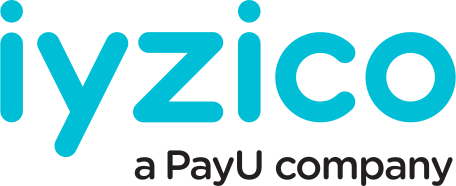
İyzico Logo Font'u Bilen?
İyzico'nun yazı fontu çok hoşuma gitti. Bu font'u bilen veya buna yakın font bilen var mıdır? Font: Yumuşak ve al benisi var.
Quicksand medium olanı dene
https://www.fontsquirrel.com/ Fontu bulma kısmından bir bakın bakalım en yakın font ne çıkıyor.
Antipasto Pro Font Family çok uygun gibi: https://www.1001fonts.com/antipasto-font.html
Ayrıca bir de Google fontlar arasındaki Nunito isimli font iş görebilir:
Özellikle extra-bol 800 'ü tavsiye ederim.